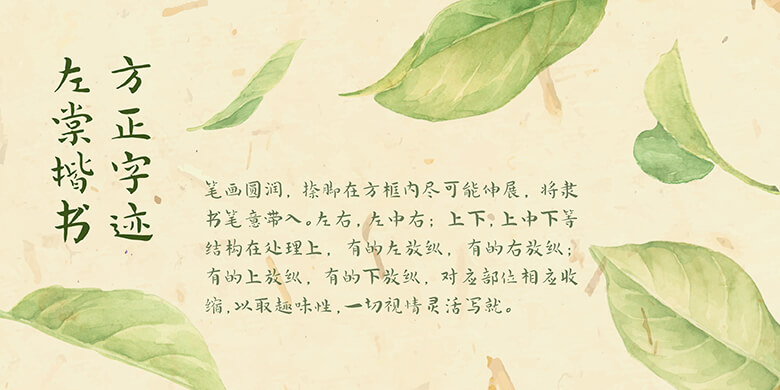
方正字迹-左棠楷书-简繁
作者杨左棠,自幼受家庭艺术熏陶,师从父亲杨建侯,并受教于萧娴等名家。现为杨建侯基金会副理事长,徐悲鸿研究会理事,江苏省书法家协会会员。楷书在我国有悠久的历史,相对于其他字体设计起来比较容易刻板。作者在设计该款字体时考虑到给楷书注入活力,就向魏晋楷书中汲取养分。笔画圆润,捺脚在方框内尽可能伸展,将隶书笔意带入。左右,左中右;上下,上中下等结构在处理上,有的左放纵,有的右放纵;有的上放纵,有的下放纵,对应部位相应收缩,以取趣味性,一切视情灵活写就。总之,在不违反字库方框字的限制范围内,强调书写性,尽可能使楷书活脱。